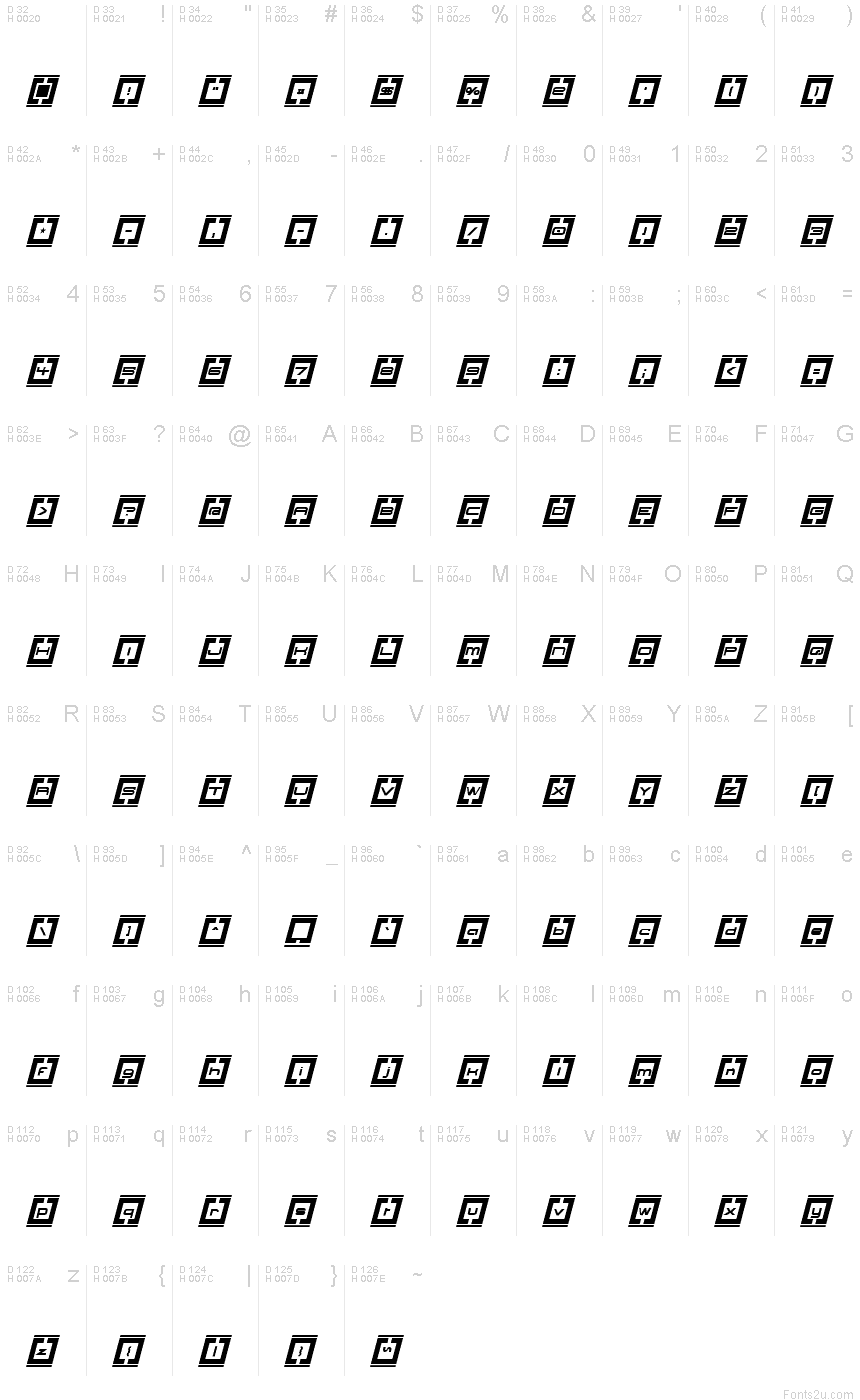
Border Base Future Italic
Border Base Future Italic من GM هو خط تقني مجاني للعناوين (Display)، يبدو وكأنه مبني من ألواح مائلة متصلة في حركة سريعة. يقع كل حرف داخل كتلته المائلة الخاصة، مع مساحات داخلية مشرقة ونظيفة تقطع الإطار الأسود الثقيل بحدة، مما يجعل النص يبدو وكأنه يتسابق عبر شاشة وحدة تحكم. يضفي الإيقاع المائل للأمام والتباعد الضيق على العناوين شعوراً بالسرعة والإلحاح والدراما الرقمية.
باستخدام Border Base Future Italic، يمكنك دفع شعارات ألعاب الخيال العلمي، وملصقات السباقات، ولافتات الفعاليات التقنية، وصور مصغرة لليوتيوب، وعلامات تجارية للرياضات الإلكترونية، وأغلفة ألبومات الموسيقى الإلكترونية إلى أراضٍ جريئة وعالية الطاقة. يتألق هذا الخط المجاني في الأحجام الكبيرة حيث يمكن لتلك الألواح الضخمة والمنحنيات الداخلية الواضحة أن تبرز حقاً. نسّقه مع خط بسيط ومحايد بلا زوائد (Sans Serif) للنص الأساسي للحفاظ على سهولة قراءة التصاميم، بينما يقوم Border Base Future Italic بالجزء الأكبر من العمل البصري.